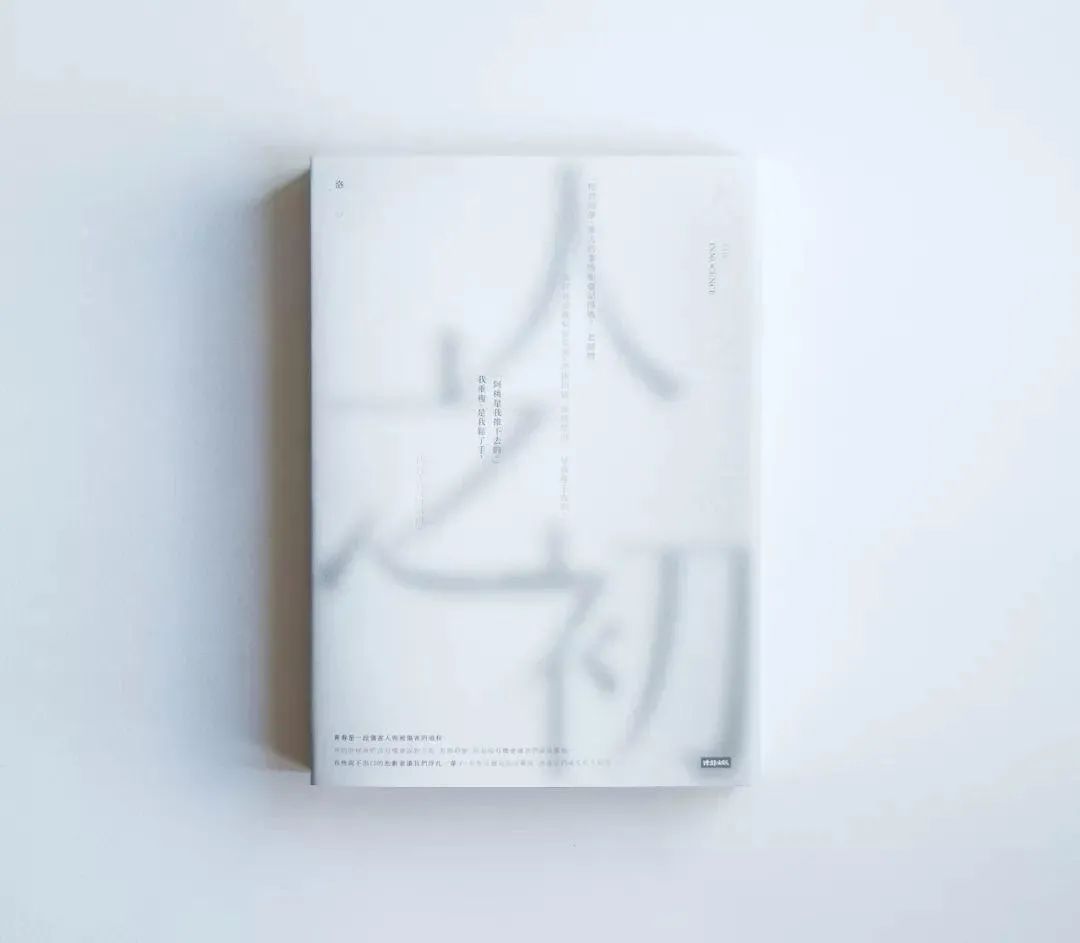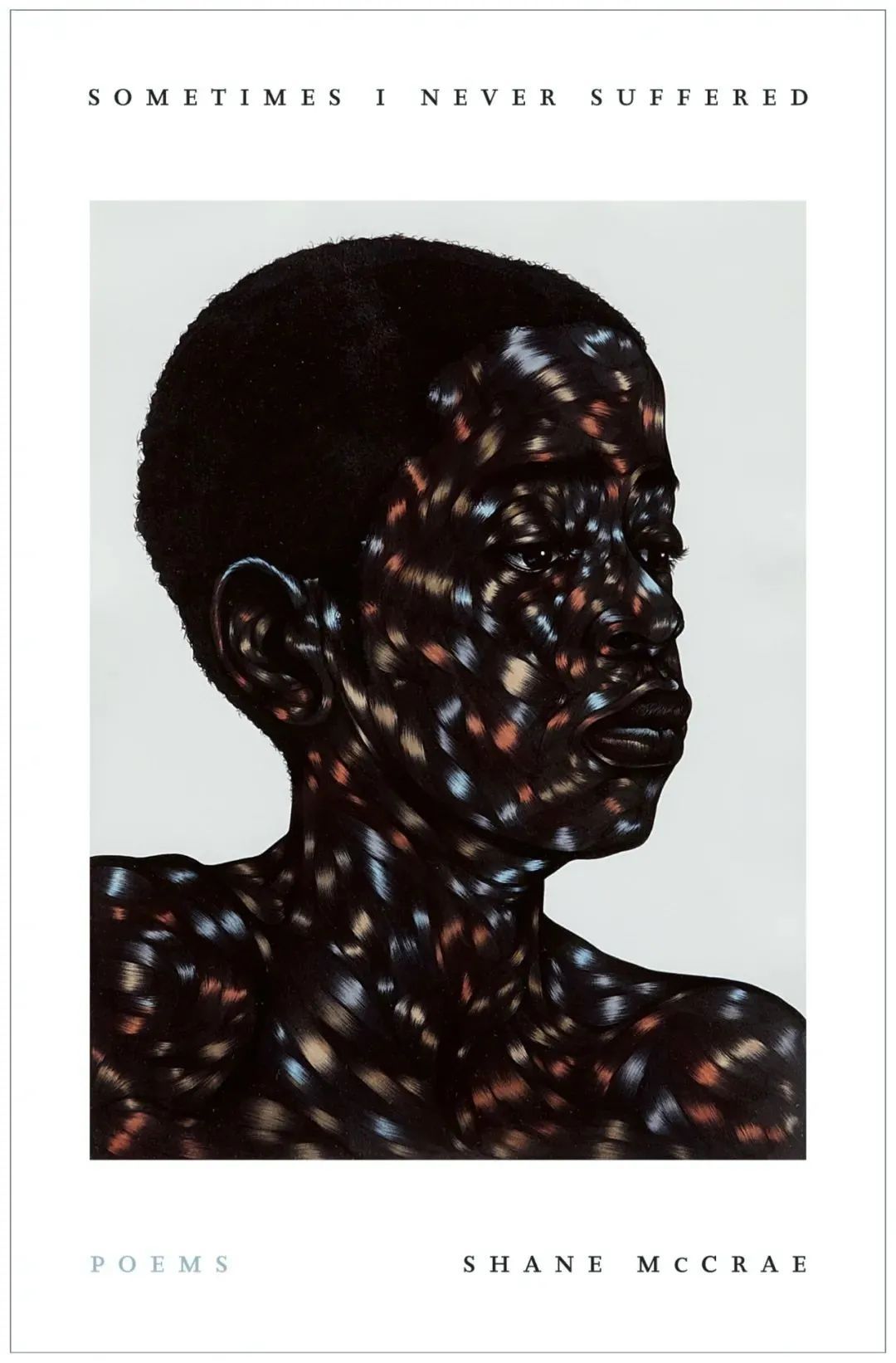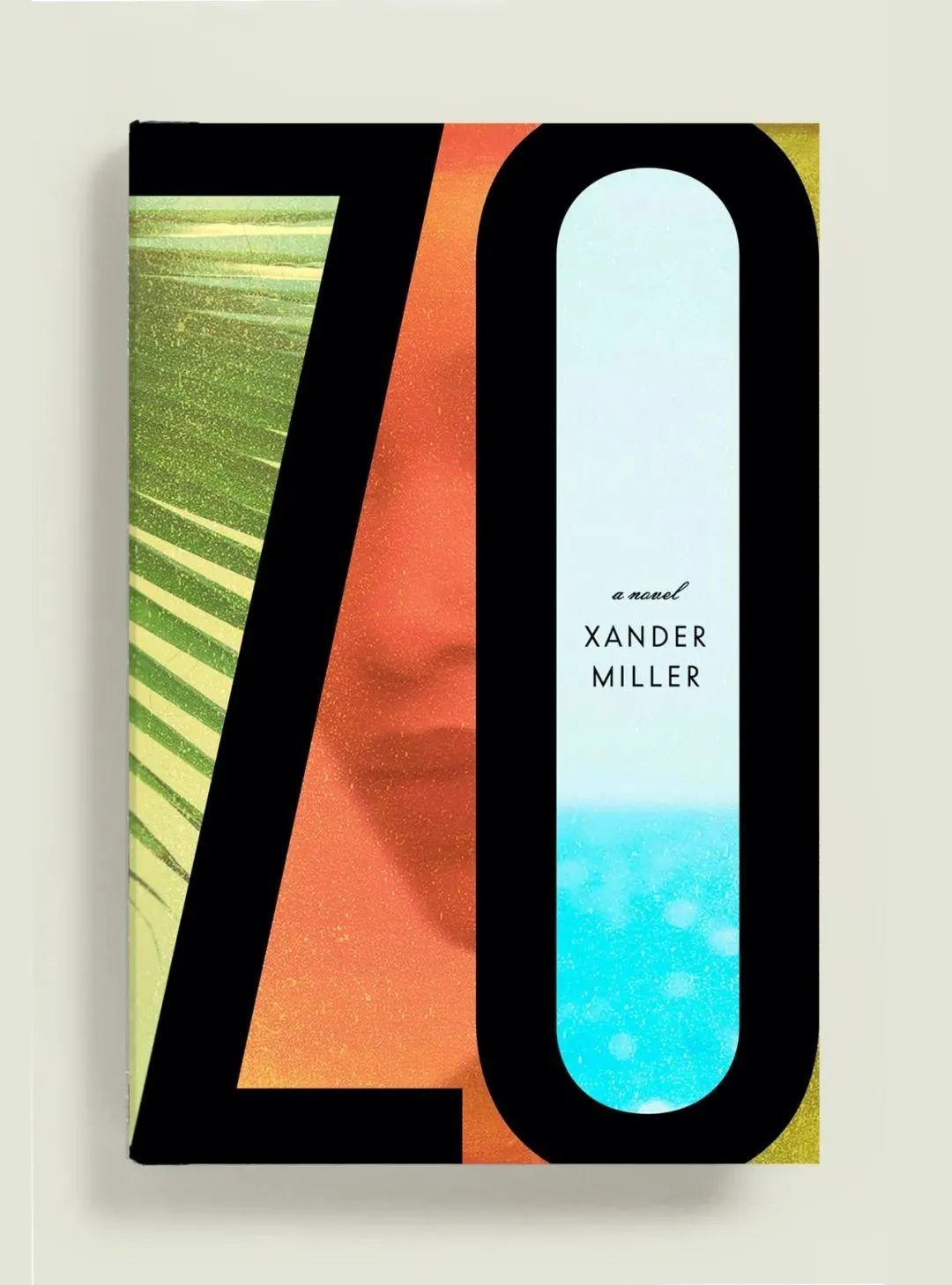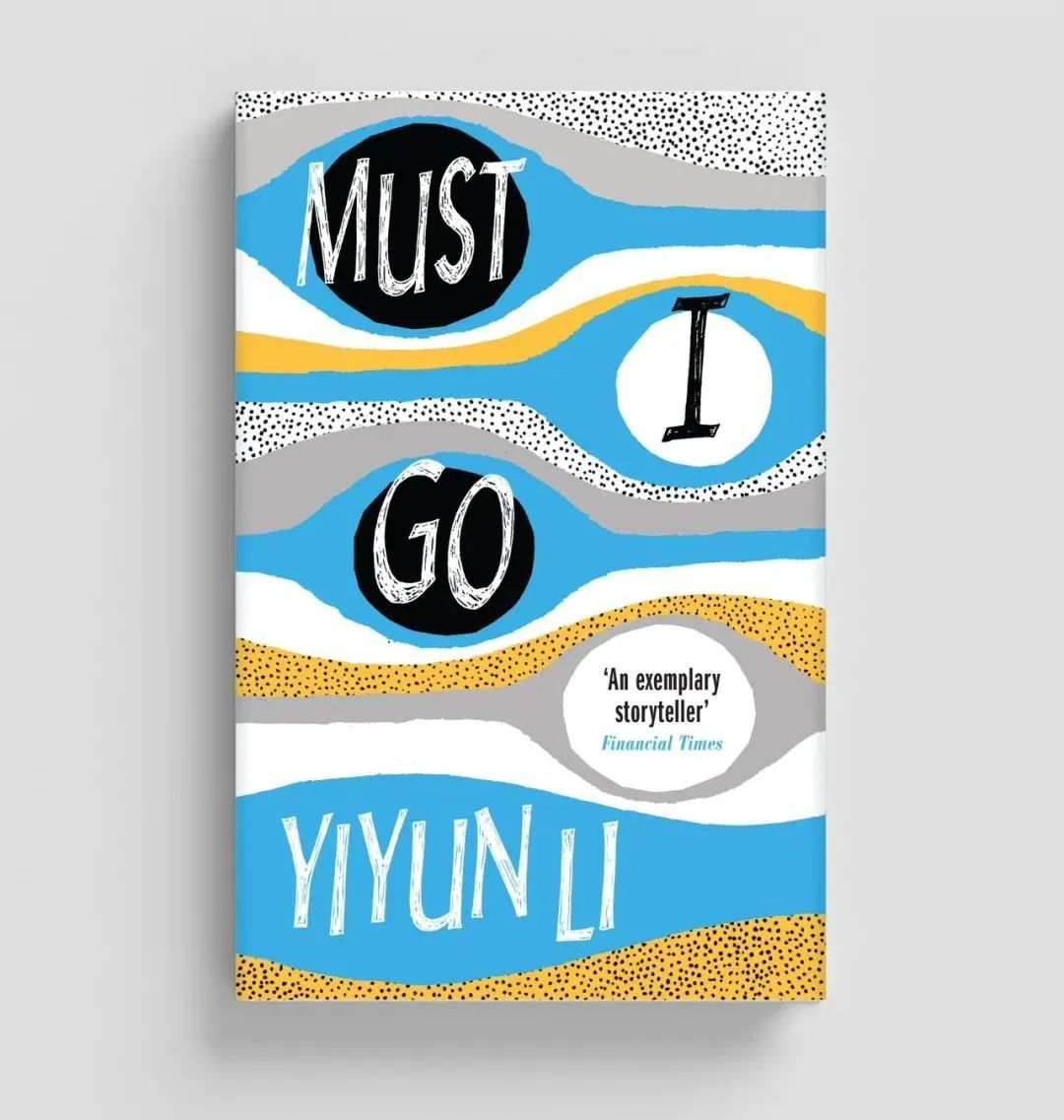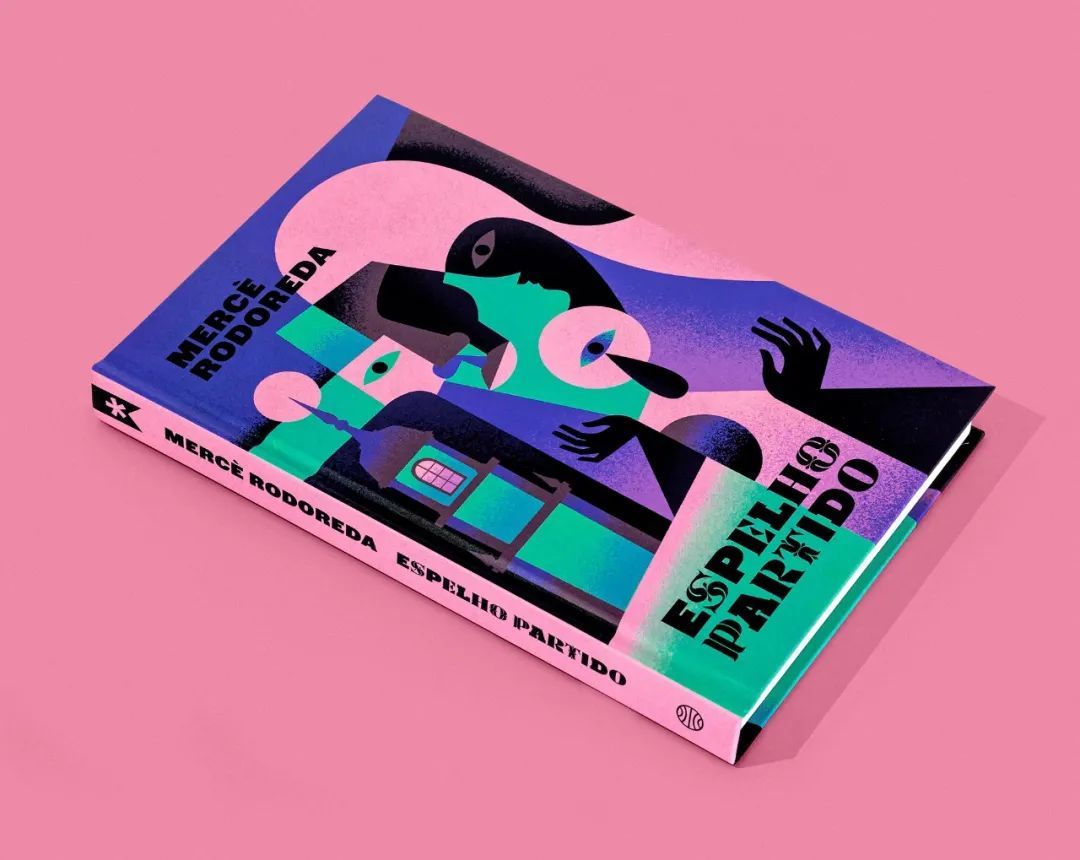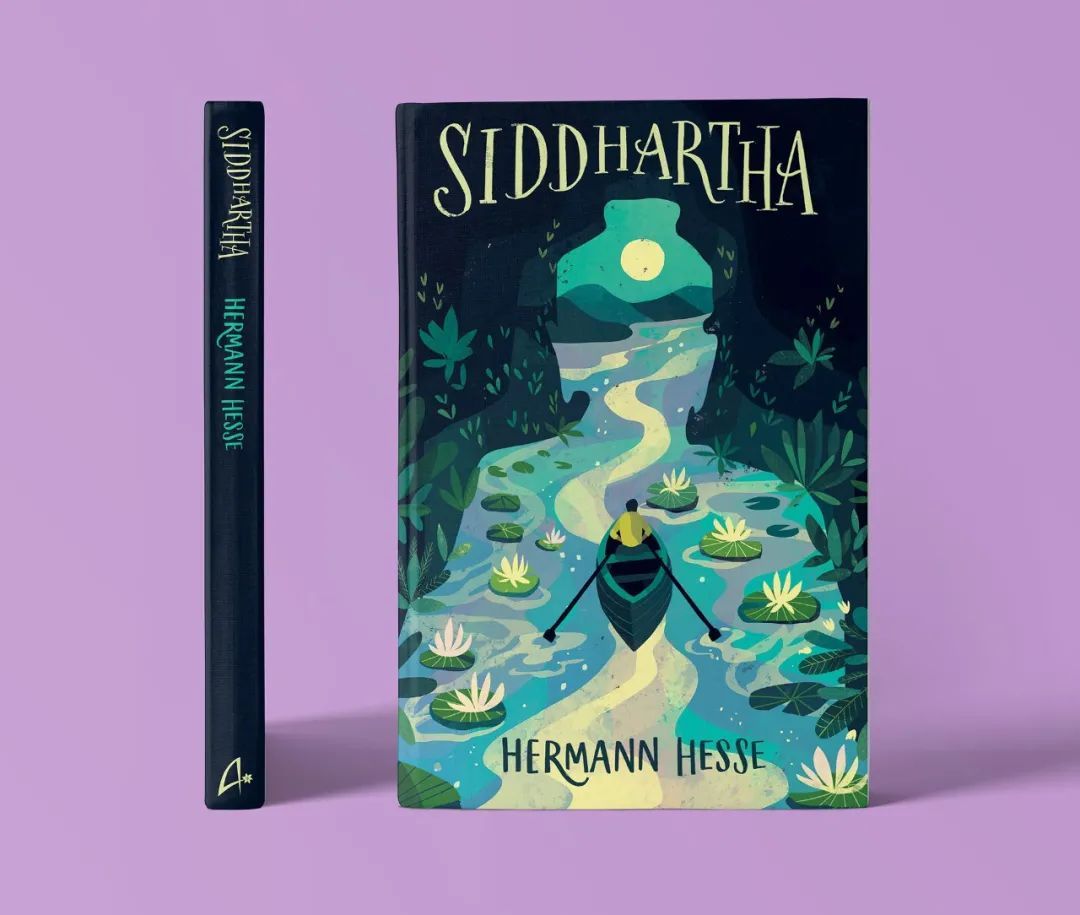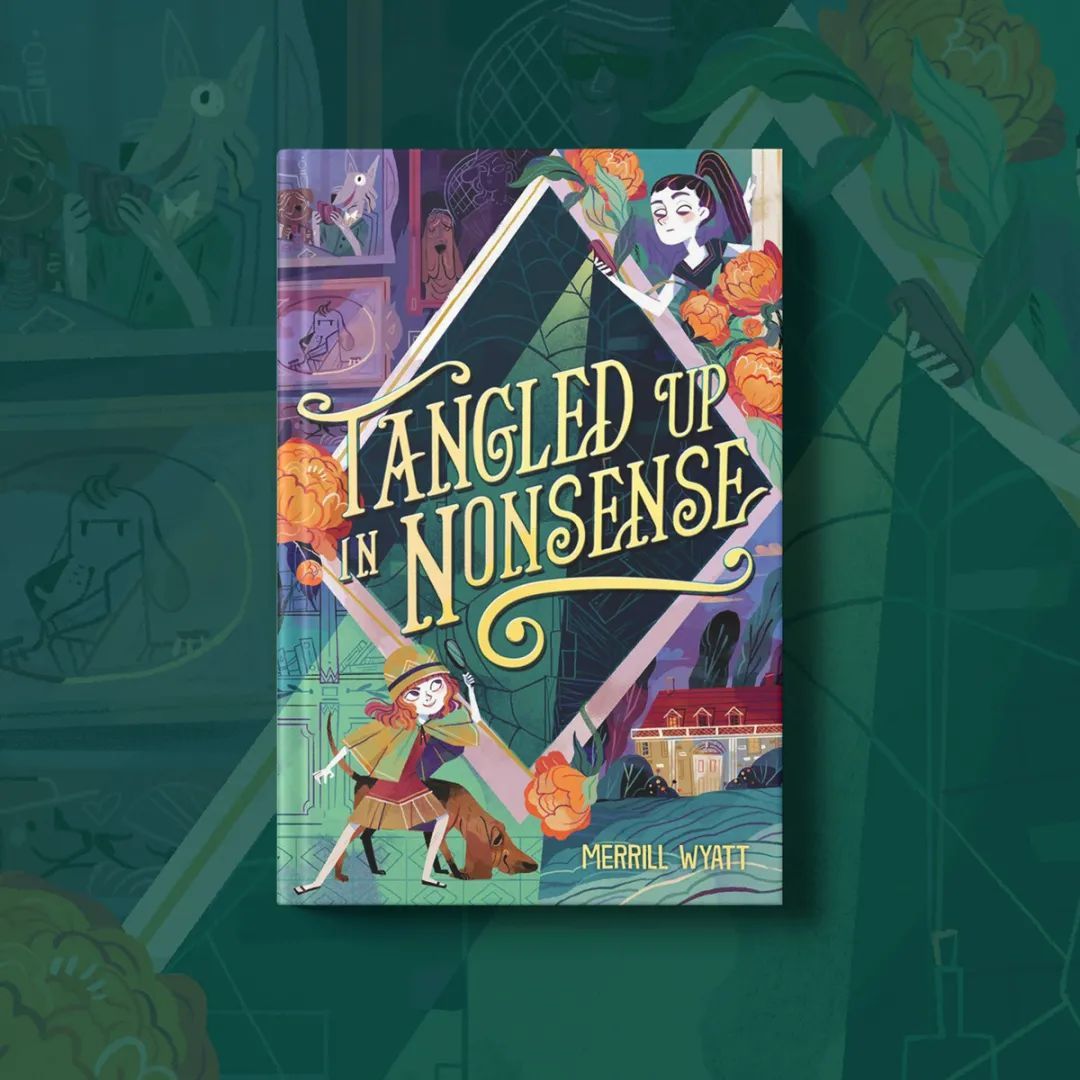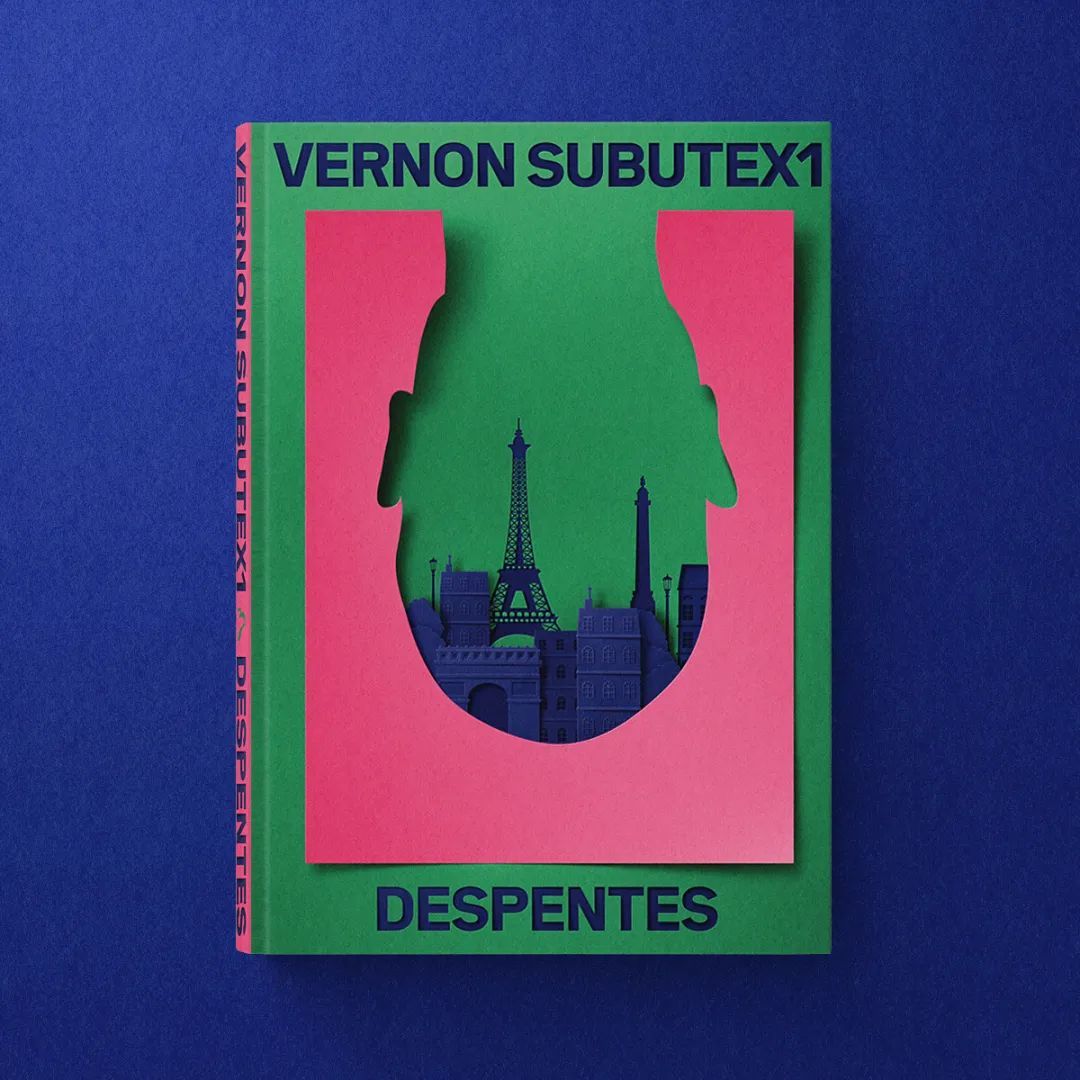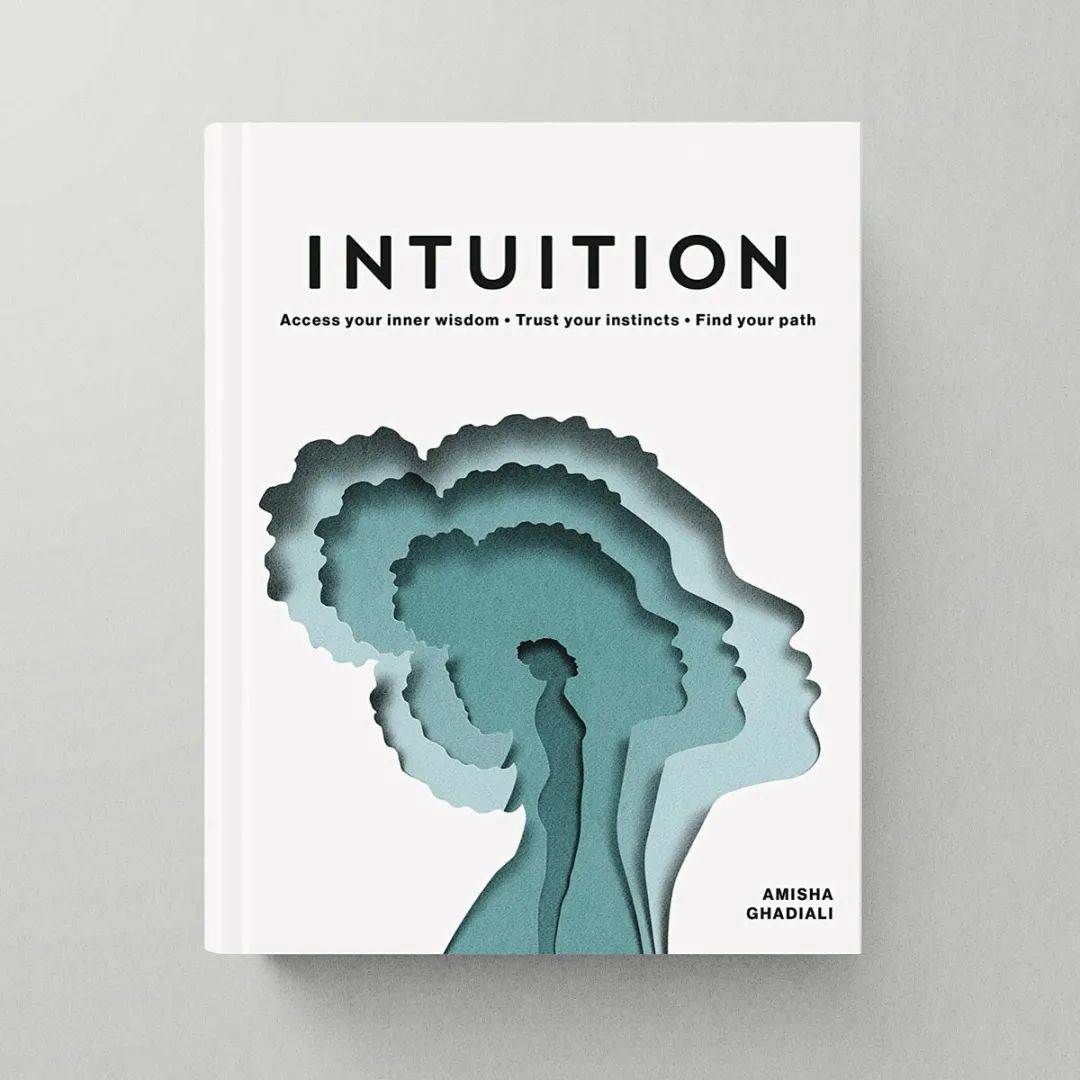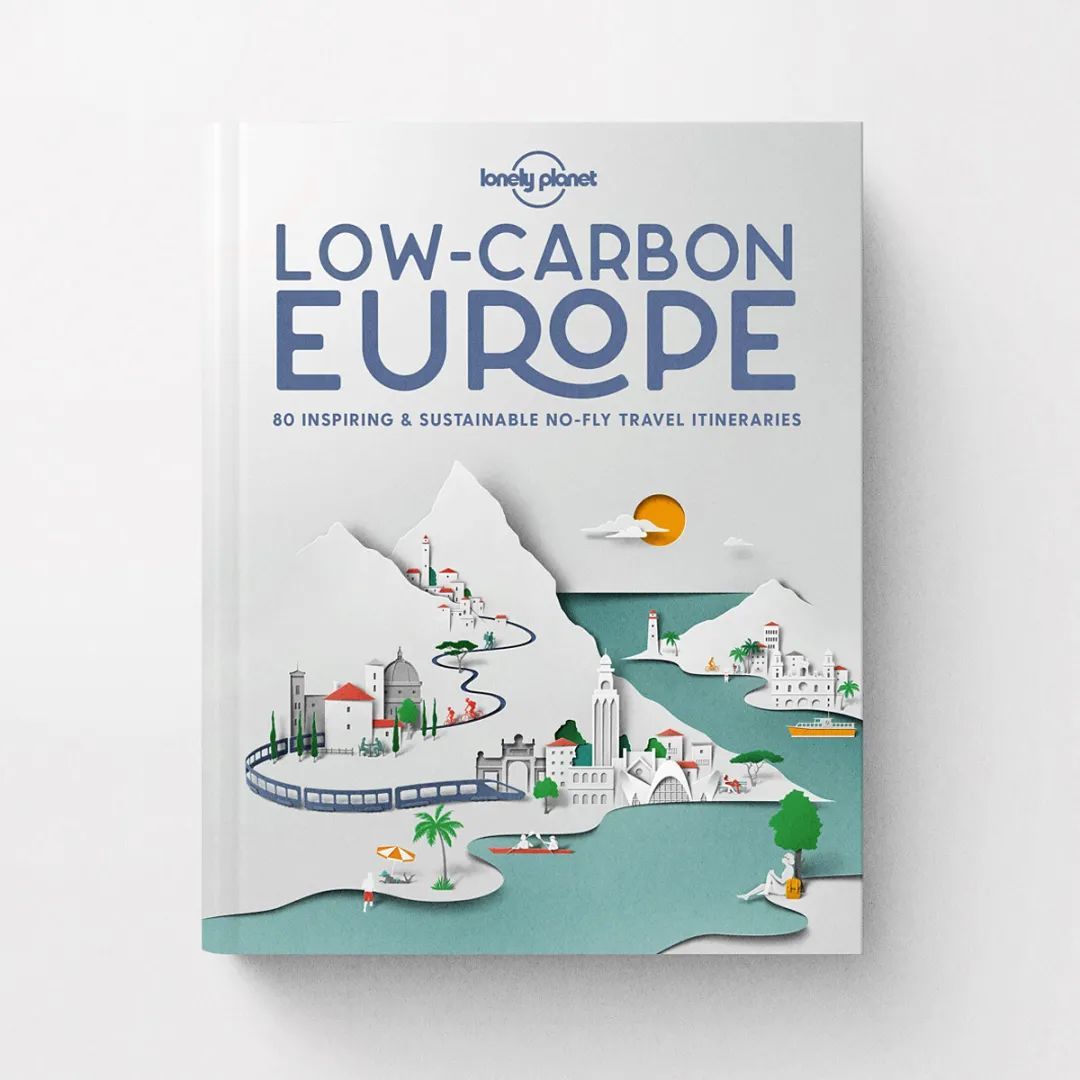
四种常见的书籍封面设计表现形式
书籍封面,是大多数读者对于一本书最初、也是最重要的印象,在当今琳琅满目的书海中,书籍封面起了一个无声的推销员作用。书籍的封面设计是书籍装帧设计的重要组成部分,它的好坏在一定程度上将会直接影响人们的购买欲。
书籍封面设计表现形式主要从图像、文字、材质工艺等方面进行设计,基本上所有书籍都需要有文字,所以特别考验设计师的文字排版能力。
今天跟大家分享一下4种常见的书籍封面设计表现形式,希望对大家有所帮助。
01— 纯文字排版
封面只有文字作为设计元素,字体一般会经过重新设计,以独特的形象呈现。
02—文字与图像排版
在封面设计中插入与内容相关的图片,这样不仅能快速传递宣传信息,突出主题,还能增加视觉效果。
03— 文字与图形排版
封面加入图形的设计,能提升画面的艺术感和形式感。比如某些主题无法用具象的图来传达概念,那么可以设计抽象的图形来表达。
04— 文字与插画排版
插画形式可以理解为经过手绘处理的图形。插画的好处在于它具有丰富的想象力和自由创造性。
封面设计,除了好看的排版,材料的选择和印刷工艺也能给封面带来强烈的视觉效果,比如UV、烫金、凹凸、丝印、覆膜、镂空等工艺。
在这个看脸的时代,大家越发习惯用选美的眼光去挑选书籍,如果没有精美且吸引人的封面及装帧设计,就吸引不了大家的眼光。